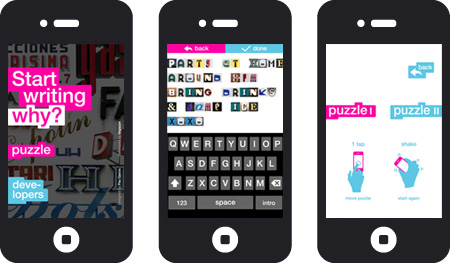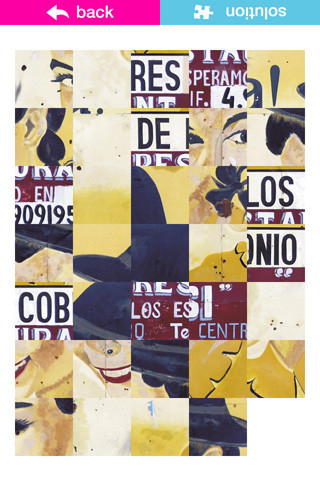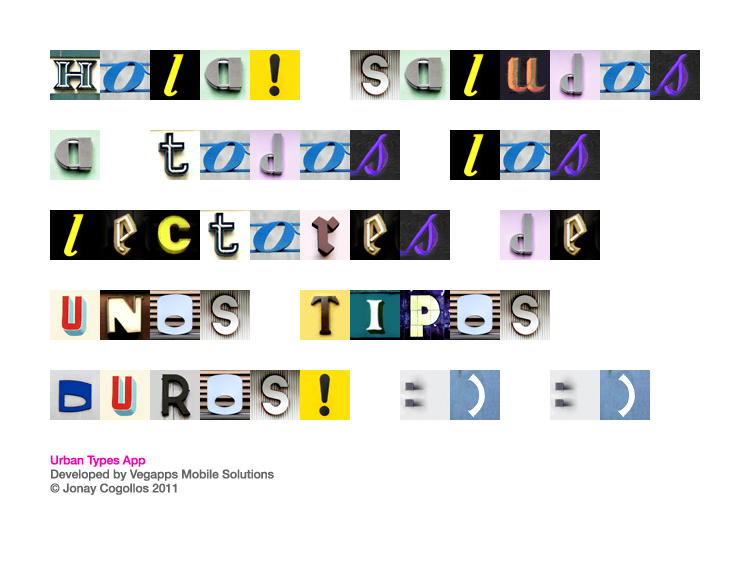
Hace unos días hicimos una pequeña entrevista a nuestro colega Jonay Cogollos, ahora compartimos por aquí.
¿Qué es Urban Types?
Urban Types (UT) es una app creada para terminales móviles y tabletas de Apple ideada y generada con el objetivo claro de hacer participe a la gente de mi interés personal por la gráfica comercial y la tipografía que encontramos en el espacio público.
Tras haber obtenido en 2011 el título de doctor europeo con mi tesis titulada La gráfica comercial del entorno urbano europeo. Interferencias en el plano sociocultural y artístico, mi intención y objetivo principal era la de compartir con los demás la belleza gráfica que encontramos a nuestro alrededor y la importancia de la tipografía como elemento definitorio del espacio en el que nos movemos. La creación de Urban Types me ayudó a conseguir dicho objetivo.
Personalmente considero que la rotulación comercial es uno de los elementos cuya importancia y transcendencia no se valora lo suficiente. La función principal de la gráfica comercial que encontramos en el espacio urbano consiste, entre otras cosas, en ofrecer información que nos permite comprender nuestro complejo entorno edificado. La gráfica comercial imprime carácter a nuestro entorno y por eso, mediante su estudio y observación, conseguimos entender un poco mejor nuestra realidad, nuestras culturas y, en consecuencia, el mundo que nos rodea.
La actividad comercial e industrial de nuestra economía de mercado y su plasmación en nuestro paisaje urbano, a través del lenguaje publicitario, configuran una determinada imagen de nuestras ciudades. Los rótulos, avisos, reclamos, vallas o la nomenclatura de los espacios ciudadanos, entre otras manifestaciones de la escritura, forman parte del tejido ambiental de la ciudad. El objetivo principal de la publicidad comercial es dar a conocer lo que el mercado ofrece a una determinada comunidad e intenta persuadir a la misma de su conveniencia para su adquisición. Su plasmación en nuestro entorno urbano queda evidenciada, en mayor o menor medida, en la rotulación comercial.
Dicha rotulación, que diariamente percibimos en el espacio publico, tiene la funcionalidad de informarnos sobre la actividad de los diferentes establecimientos comerciales que se encuentran en nuestro entorno y constituye un campo de estudio no tan efímero como los carteles publicitarios, los “periódicos” gratuitos, los folletos que pueblan los limpiaparabrisas de nuestros coches o las banderolas que varían en función de las actividades temporales que se desarrollan en la ciudad.
Los rótulos forman parte del tejido ambiental de la ciudad y su importancia estriba en que nos vienen impuestos, en ocasiones, incluso mucho tiempo después de haber cumplido su función primordial. Es frecuente que pervivan tras el cierre del negocio (el anuncio sobrevive al anunciante) y, pese a haber perdido su sentido de mensajes comerciales, su presencia gráfica sigue formando parte de la trama visual de la ciudad. Algunos rótulos viejos crean hermosos efectos a través del tiempo: permanecen durante años degradados por los efectos del medio ambiente como testigos de otros tiempos; se caen a trozos, se difuminan y deterioran; son elementos de nuestro tejido urbano tanto como los edificios que lo conforman. Por tanto, los rótulos anunciadores forman parte del patrimonio colectivo de la ciudad y de sus ciudadanos.
A través de la generación de un abecedario que es resultado del ensamblaje de letras de la calle, UT nos permite precisamente conferir importancia a ese discurso personal que tanto me cautiva e interesa. La elaboración de mensajes tipográficos, los juegos de letras y los puzles que se desarrollan en la app me ayudan a conseguir que la gente sea consciente de la realidad de su entorno.
Mediante un método lúdico, sencillo y quizás también didáctico, centro la atención en un ámbito que personalmente me apasiona. Una muestra de ello también la podemos encontrar en mi web personal www.jonay.net , centrada básicamente en el estudio y disfrute de la tipografía como elemento artístico y a la par que creativo.
¿Quiénes integran el equipo de UT?
UT surge de una colaboración con Vegapps, una agencia de marketing móvil especializada en apps para smartphones y tabletas formada por un equipo joven con experiencia en desarrollo de software, marketing, comunicación, dirección de arte y diseño gráfico. Con su inestimable ayuda y su enorme apoyo y predisposición para colaborar y materializar proyectos interesantes ha sido posible desarrollar este gran trabajo. Estoy muy agradecido!
¿Cuáles son los alcances del proyecto?
La verdad es que estoy muy satisfecho por la repercusión que está teniendo UT a todos los niveles. El alcance de una app se puede medir de muchas maneras pero yo destacaría la importancia que tiene no solo la cantidad de descargas por parte de los usuarios, sino también su utilización continuada en el tiempo, que la app no es una aplicación de “usar y tirar”. Constatar que muchos usuarios mantienen la app en sus termines móviles después de un primer uso me hace muy feliz. También era muy importante para mi conseguir que la app fuera gratuita y que no incluyera banners o publicidad de ningún tipo.